黑体字横竖粗细一致,方头方尾,没有多余的笔画装饰,字形紧聚且没有弧线,属于非衬线字体的一种。黑体字给人以简洁明快、严肃庄重的性格体现。在现有的很多字形设计中都遵循了黑体字的基本风格。
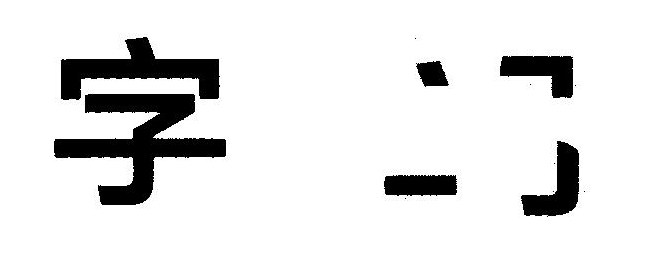
宋体字在笔画起始和结束的地方都有衬线装饰,而且笔画呈现出横细竖粗的变化特点属于衬线字体的一种。宋体字不像黑体那样严肃庄重,给人以古朴清秀之感,适合表现传统气息的字体设计题材。
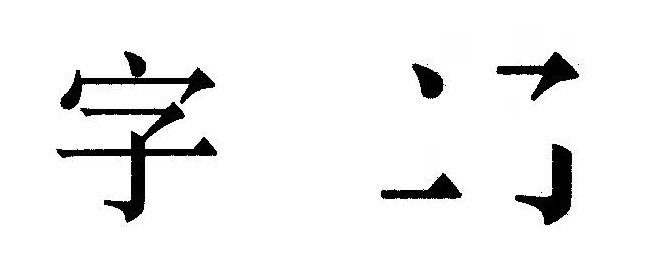
圆体字笔画没有衬线,笔画粗细一致且笔画边角呈圆角形态。圆体貝有柔美温和的性格,因此不太适合用在严肃的字体设计中,多用于女性等主题设计当中。